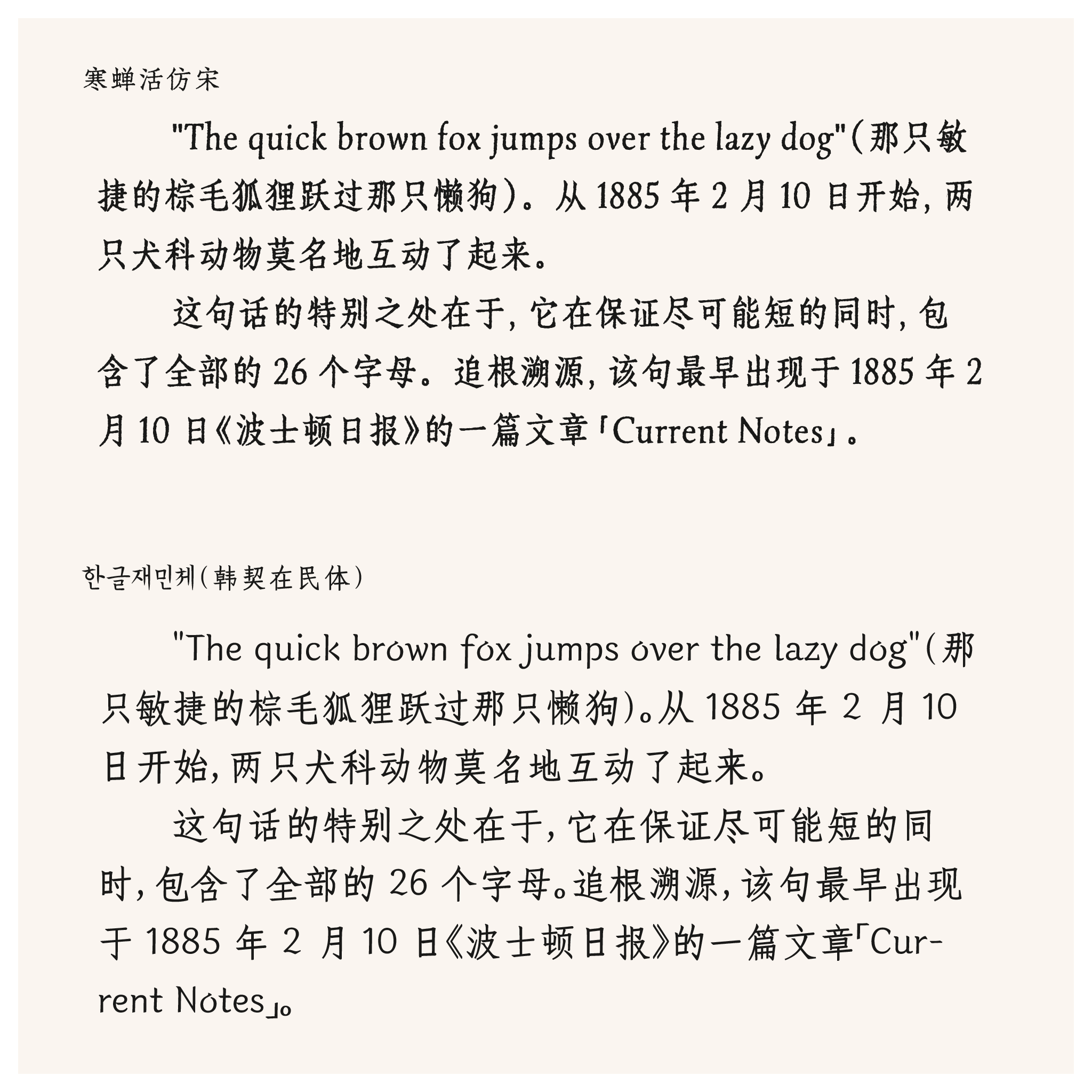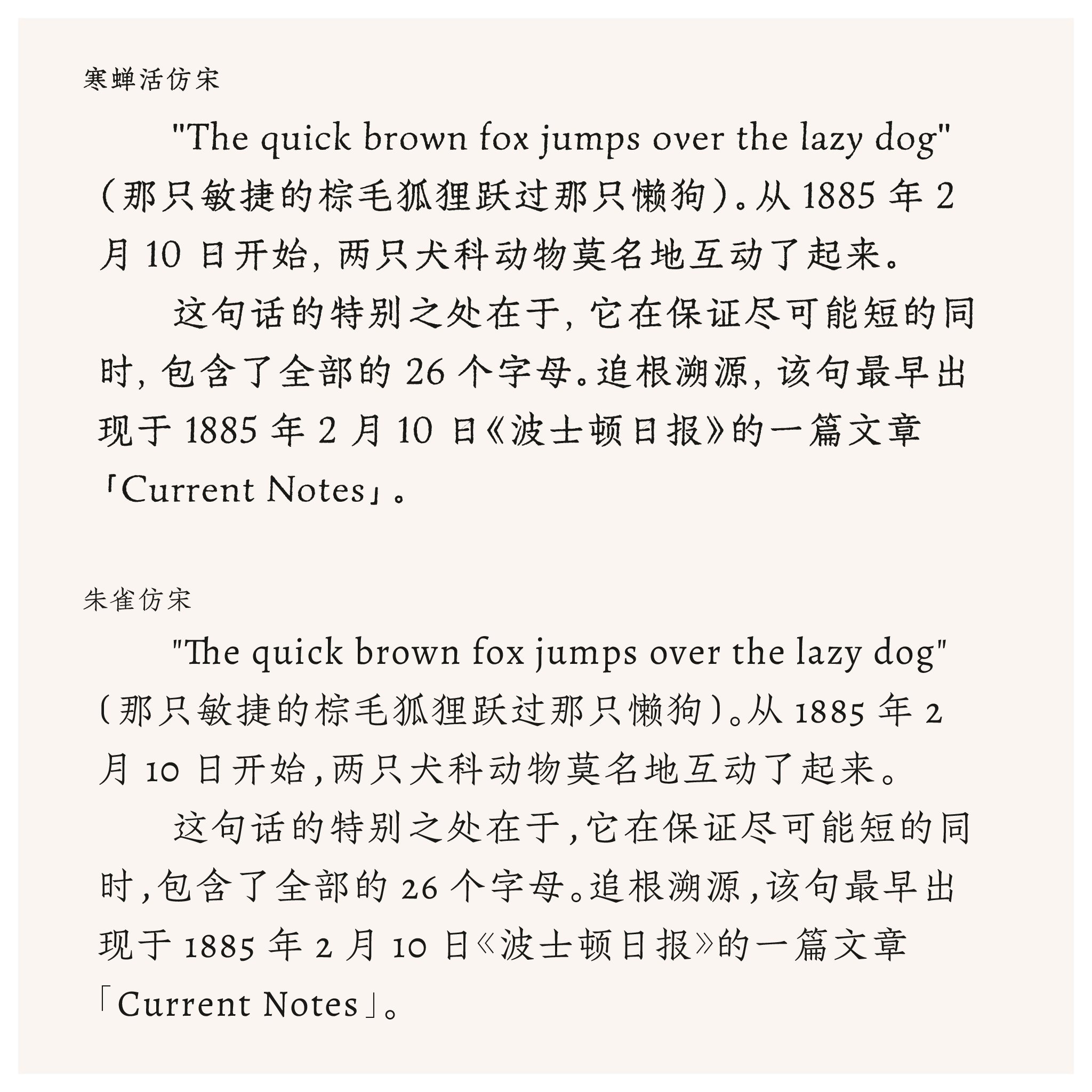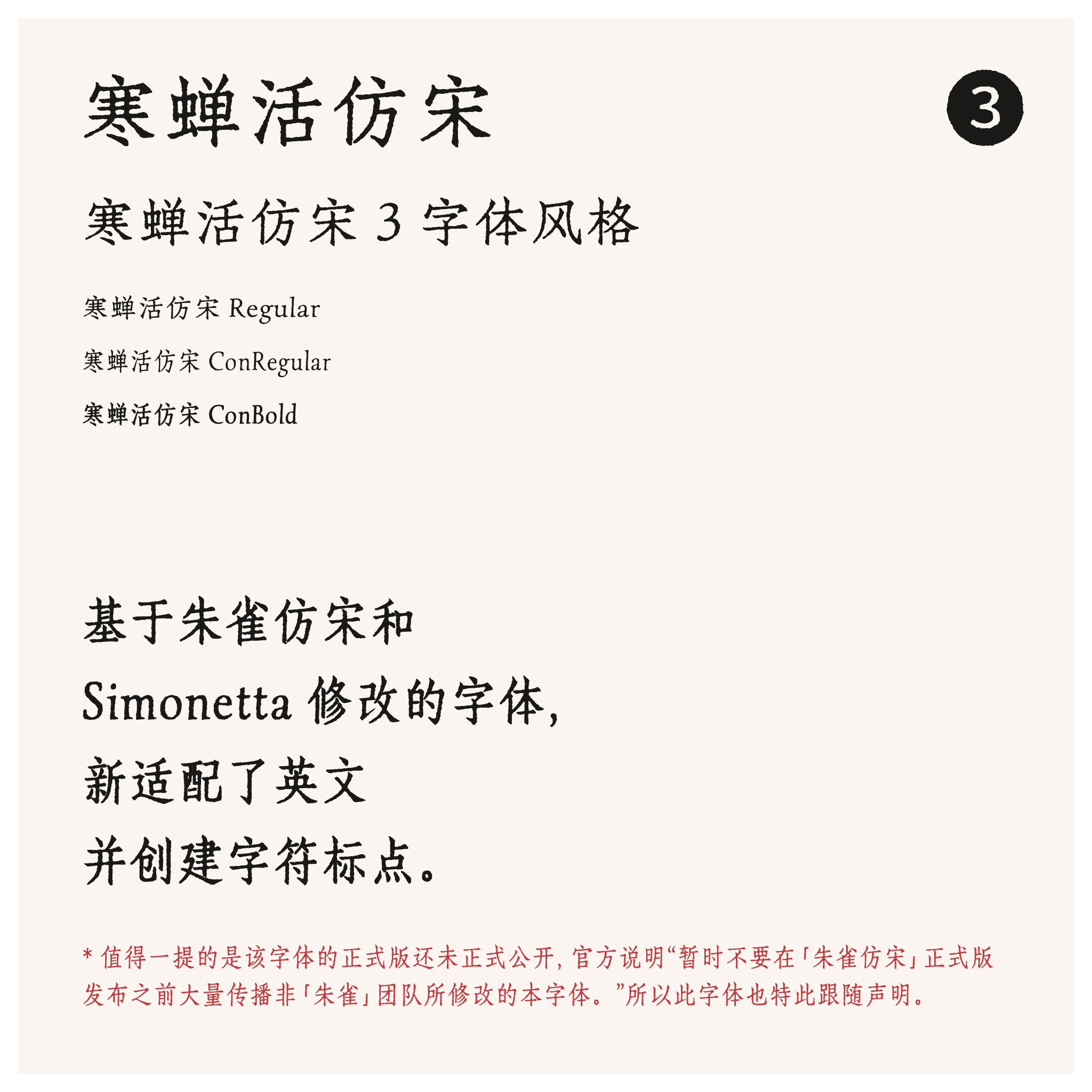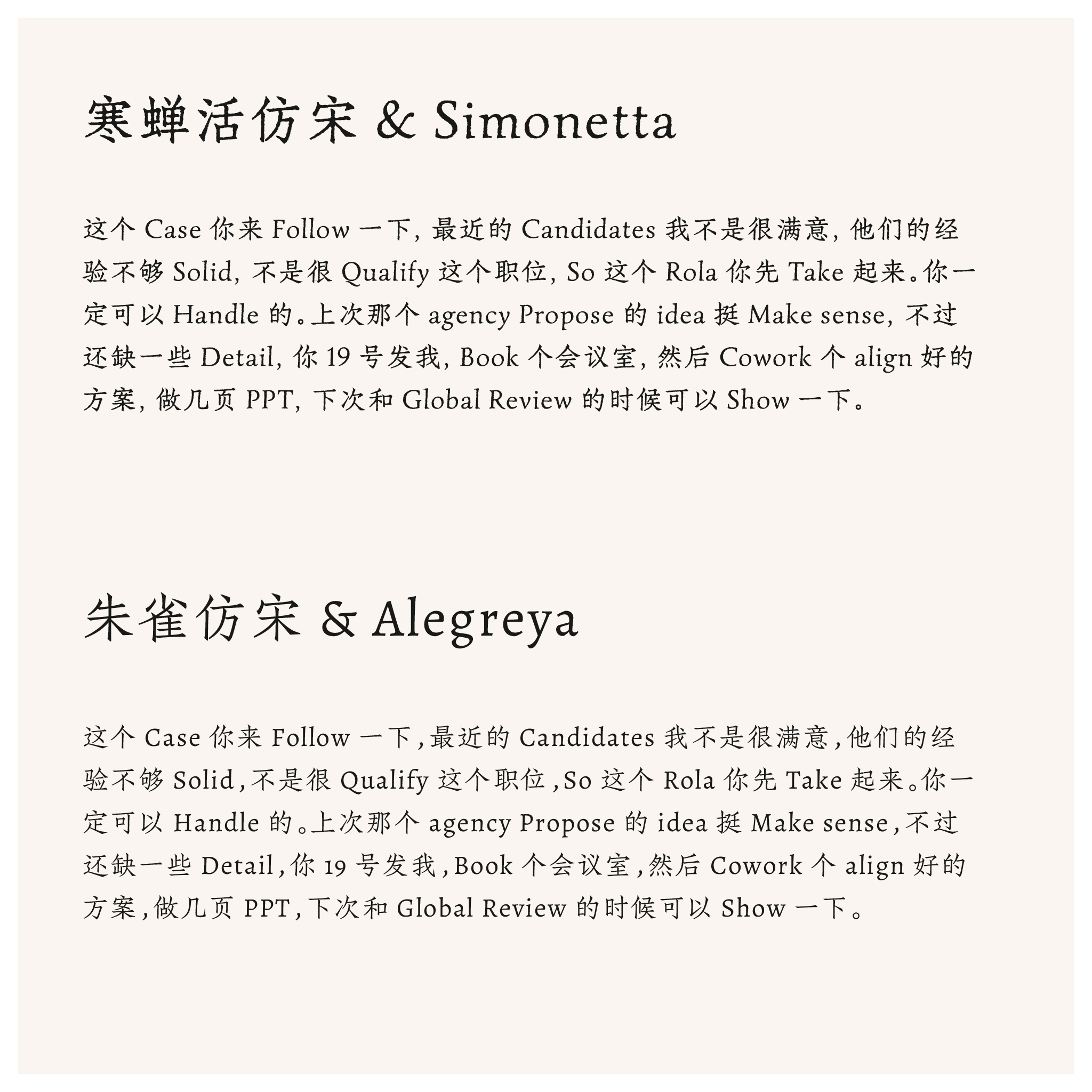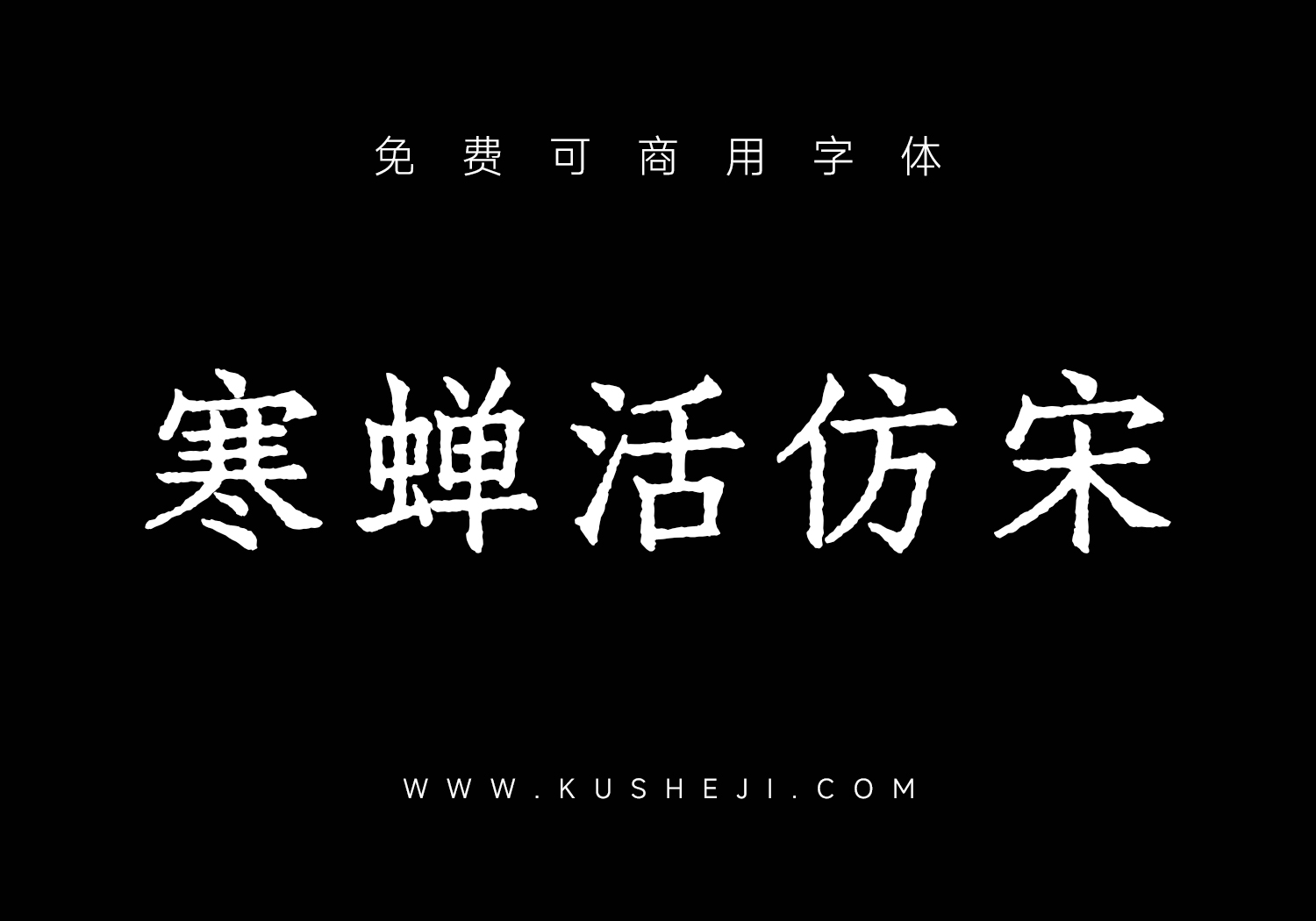
寒蝉活仿宋:免费可商用中文字体下载 2025-07-06 精选字体 226 寒蝉活仿宋是基于朱雀仿宋和Simonetta修改的字体,新适配了英文,并创建字符标点,包含3字重。 资源下载百度网盘:立即下载天翼云盘立即下载(访问码: 4pvm)复制下载地址失效请联系右侧客服补链文件类型:TTF资源大小:25MB兼容软件:Win/Mac商业许可:免费可商用来源:https://github.com/Warren2060/ChillMovableType 常见问题 素材可以商用吗,会不会有版权问题?除特殊说明之外,本站所有素材仅限学习交流,不可商用! 百度网盘下载慢怎么办?国内只有在百度网盘存放资源相对靠谱,基本不会出问题,如果是非会员建议使用天翼云盘下载资源,完全免费不限速。 原文链接:https://kusheji.com/fonts/28360.html,转载请注明出处。 0 0 免费字体可商用字体